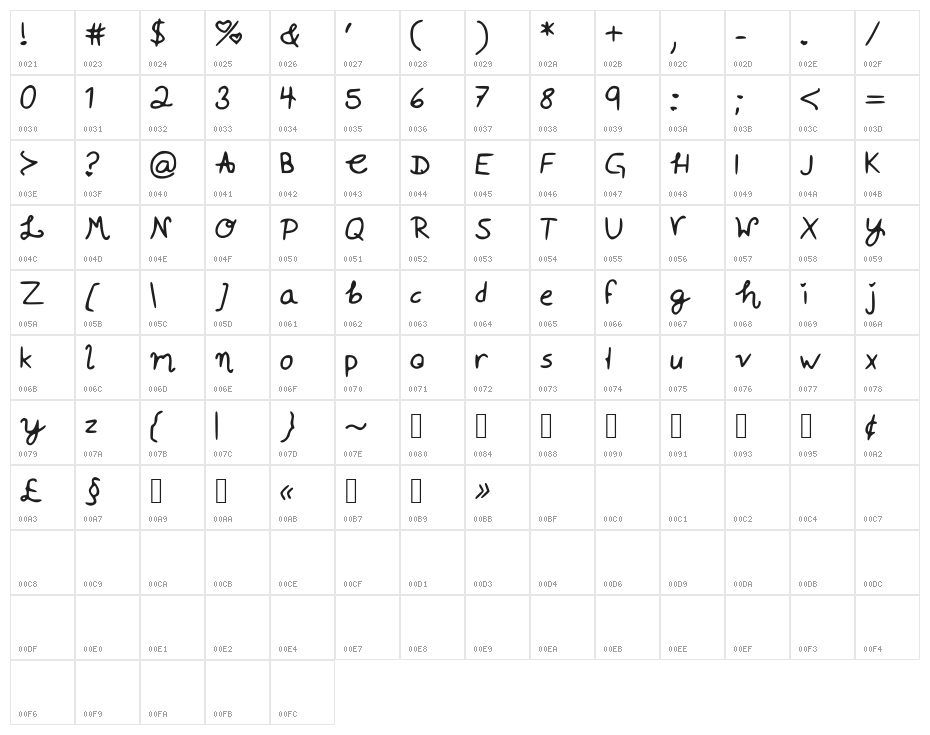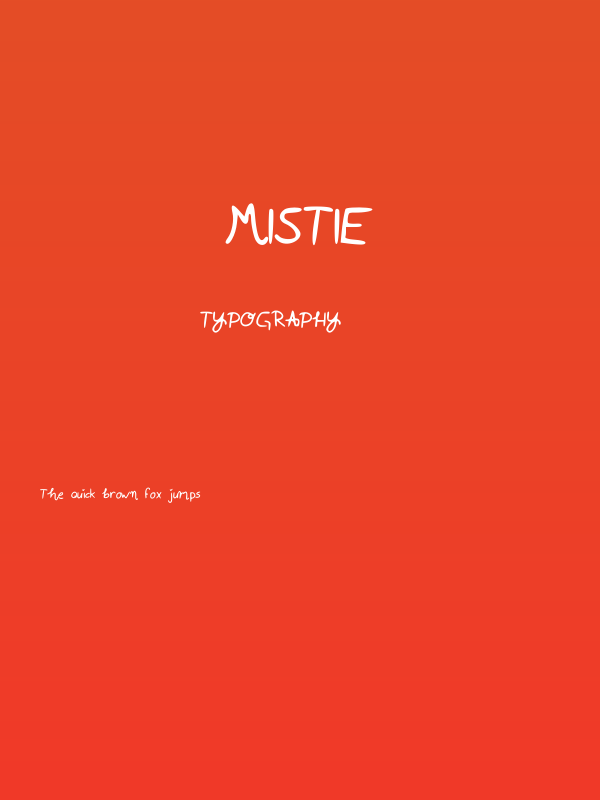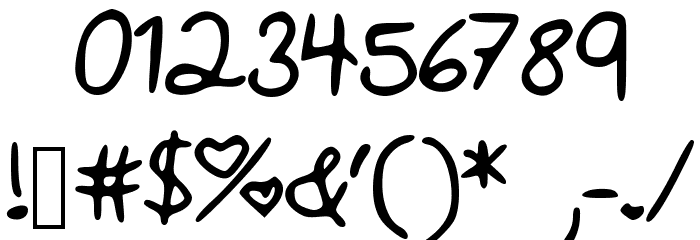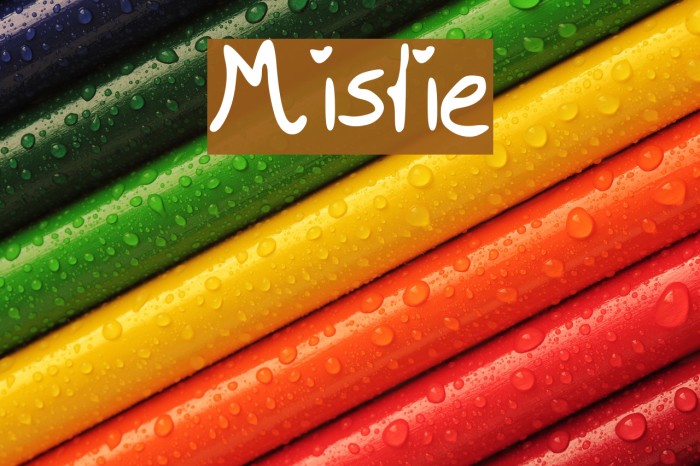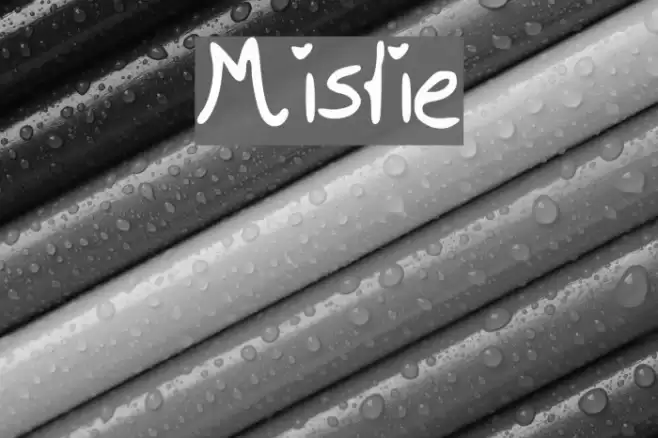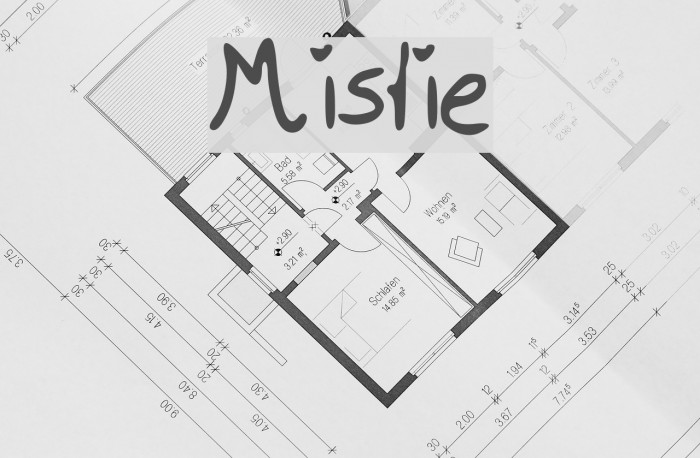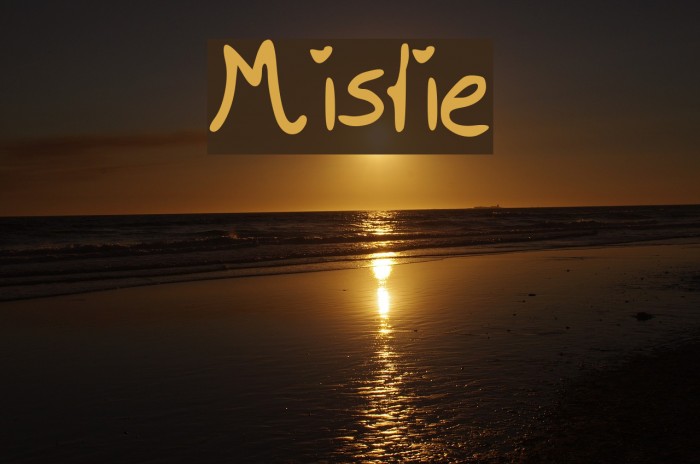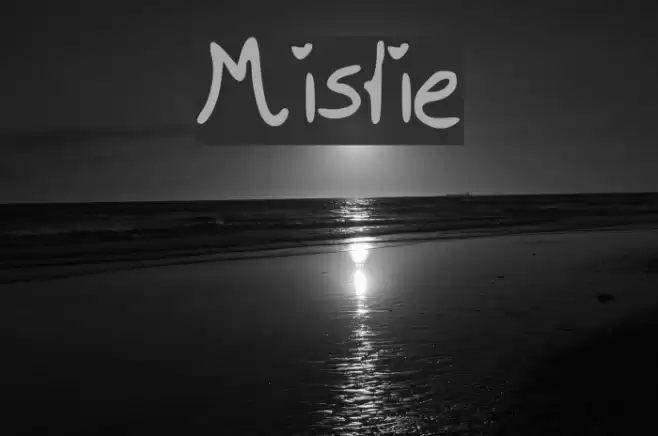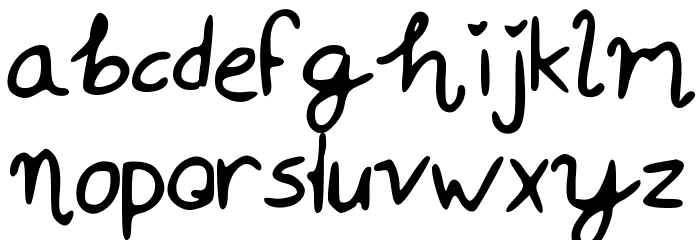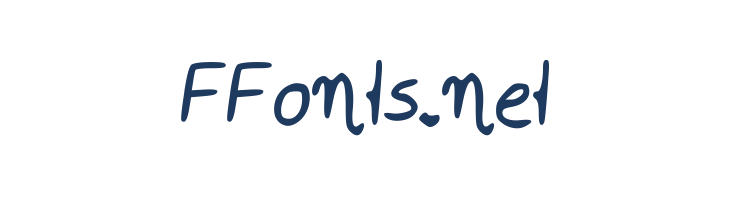
Mistie Font
| Style général | Casual, Playful |
| Cas d'utilisation | Headlines, Logos, Informal Text |
| Projets proposés | Ideal for greeting cards, children's books, playful branding, and casual invitations. |